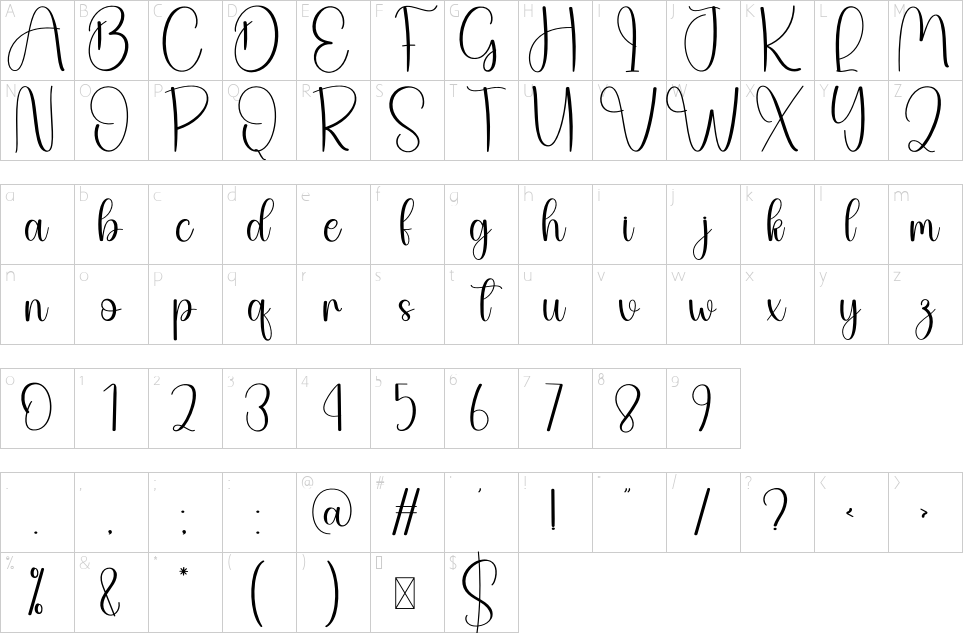
Aqui está uma descrição em português para a página de download da font ‘Deary’: Descubra agora Deary, uma fonte elegante e versátil especialmente adequada para projetos digitais modernos. Desenvolvida por scratchones, Deary foi projetada para ser usada tanto no Windows quanto na plataforma Mac. Esta fonte grata vem em um formato fácil de usar que facilitará a sua inserção em sites e documentos. Ideal para design pessoal ou corporativo, Deary oferece uma experiência visual única e sofisticada, proporcionando uma variedade incrível de opções para personalizar seus projetos digitais. Não perca essa oportunidade de adicionar um toque único à sua produção digital, graças ao design cuidadosamente pensado por scratchones. Com apenas 540 downloads até o momento, Deary já demonstrou seu potencial e versatilidade. Seja você uma profissional ou um amante do design que busca estilos únicos, não hesite em experimentar esta fonte gratuita e de alta qualidade.